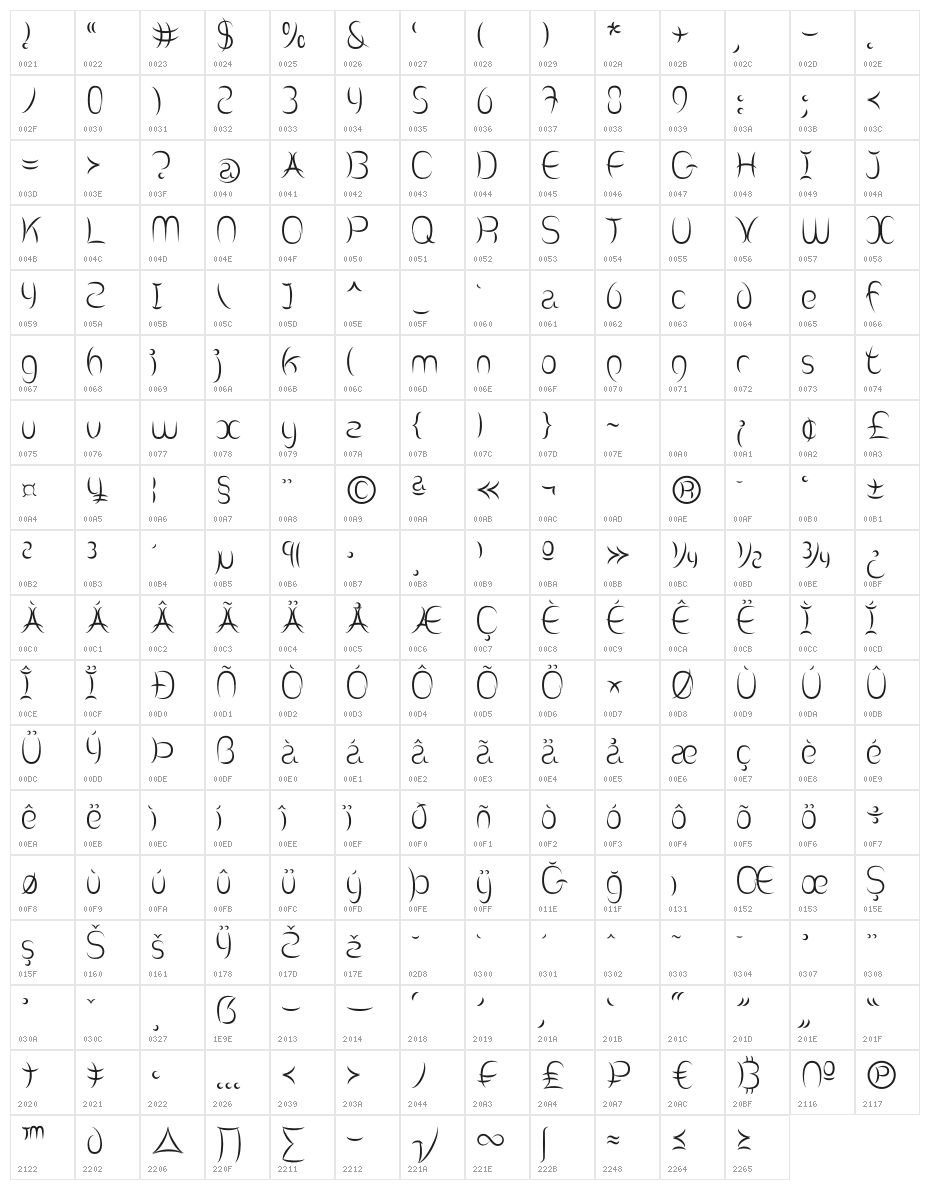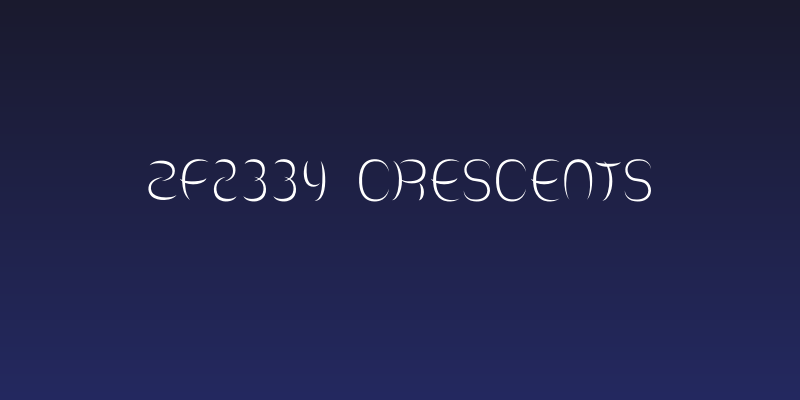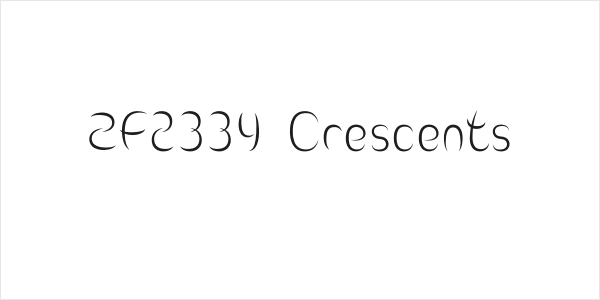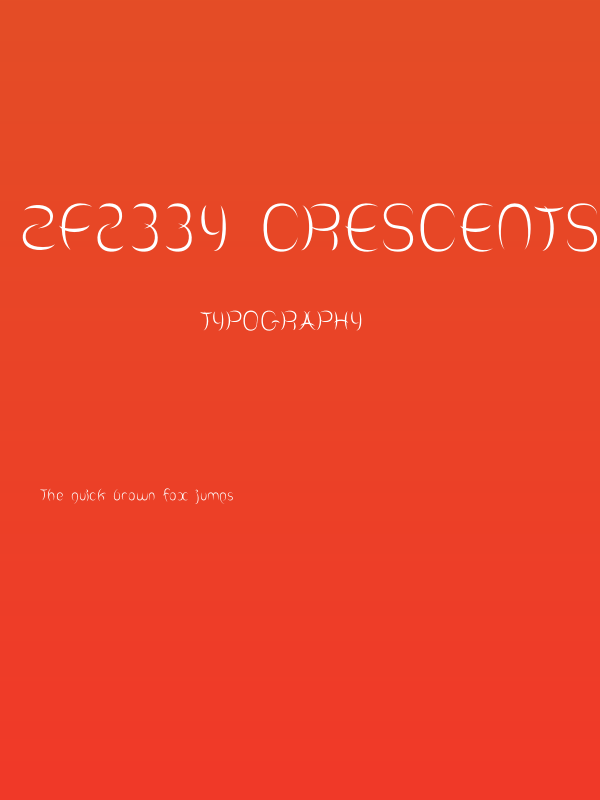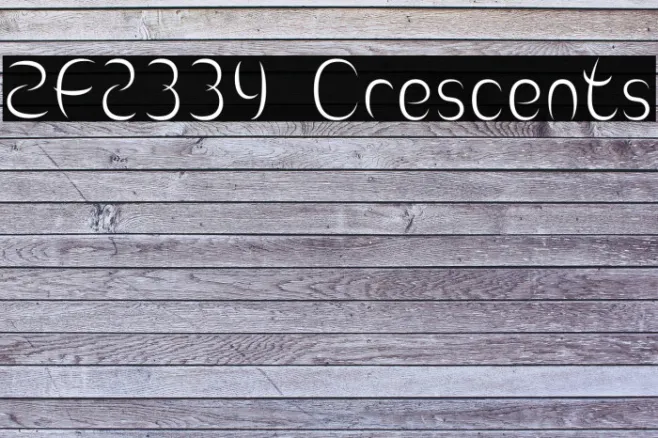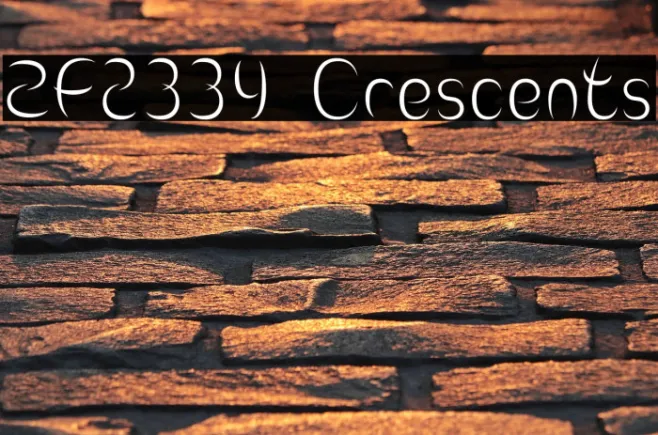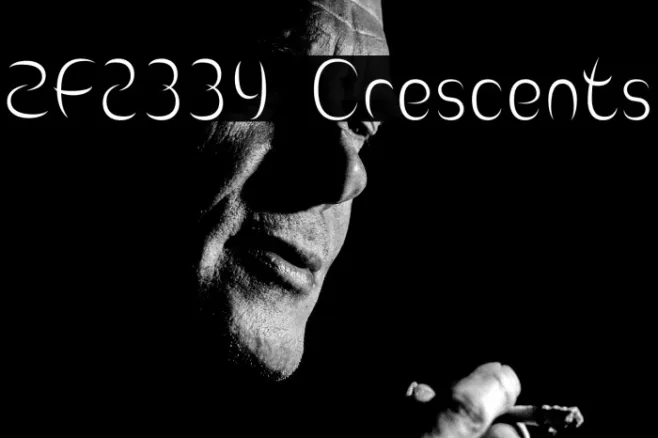
ZF2334 Crescents Font
| Gesamtstil | Decorative, Whimsical, Artistic |
| Anwendungsfall | Logos, Posters, Headlines, Invitations |
| Vorgeschlagene Projekte | Children’s books, fantasy posters, party invitations, branding for creative businesses, themed event materials. |